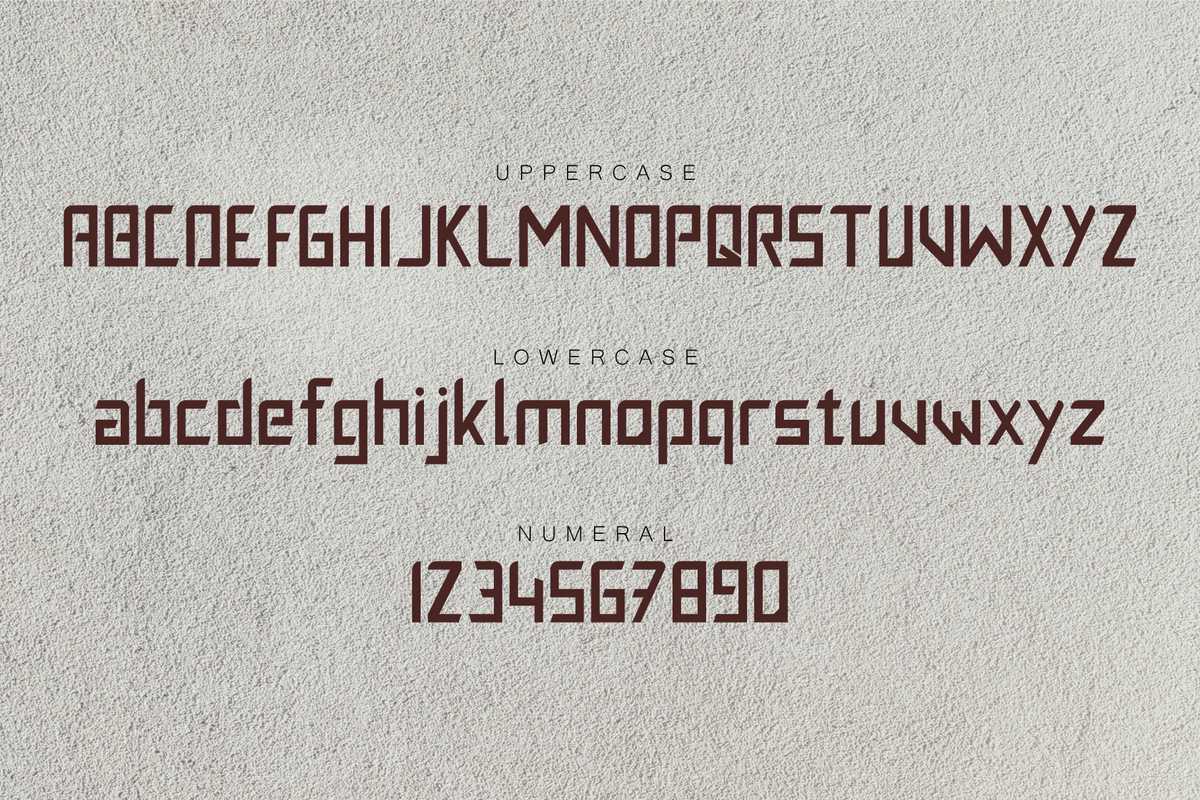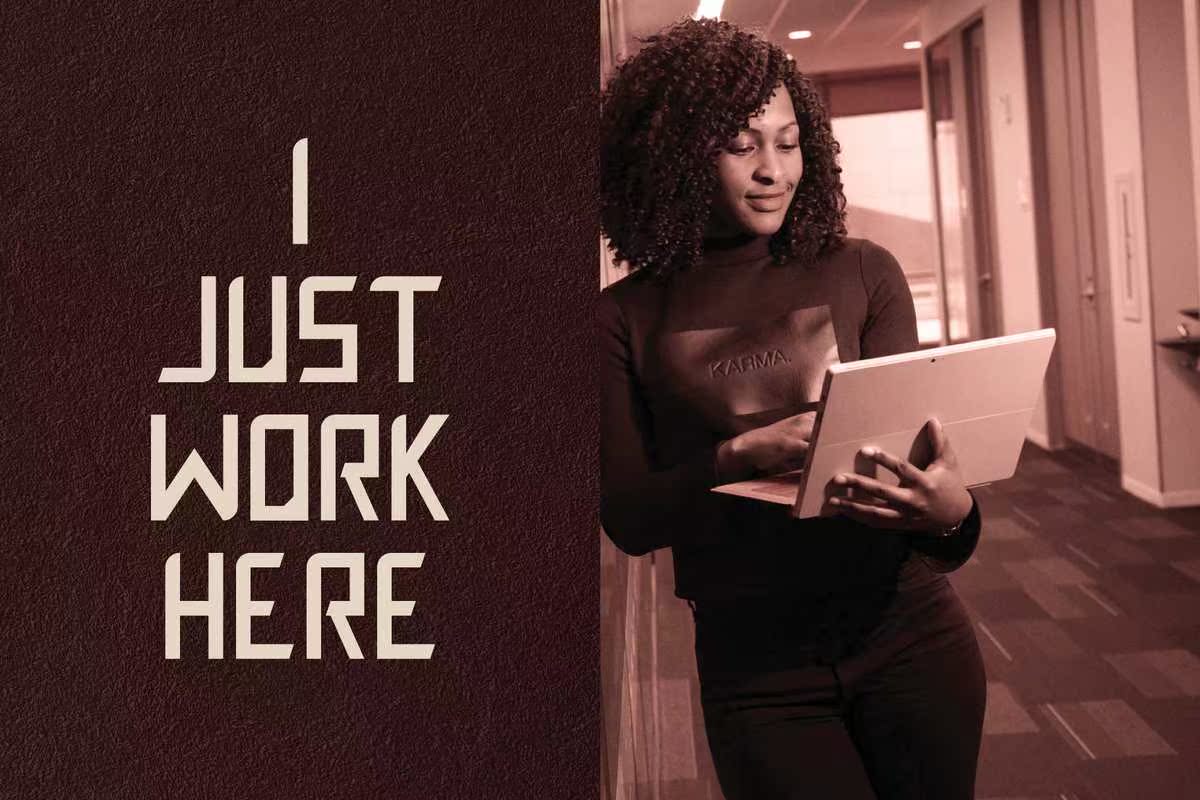
XenIt–SansSerif是带有SolidFont文件的现代NSSerif。它通过组合各种样式,以CompactSolidFont为基础。适用于徽标、贺卡、报价、海报、品牌、名片、文具、设计标题、博客标题、艺术报价、排版。XenIt–SansSerif是带有SolidFont文件的现代NSSerif。它以CompactSolidFont为基础,通过组合各种样式。适用于徽标、问候卡、报价、海报、品牌、名片、文具、设计标题、博客标题、艺术报价、排版